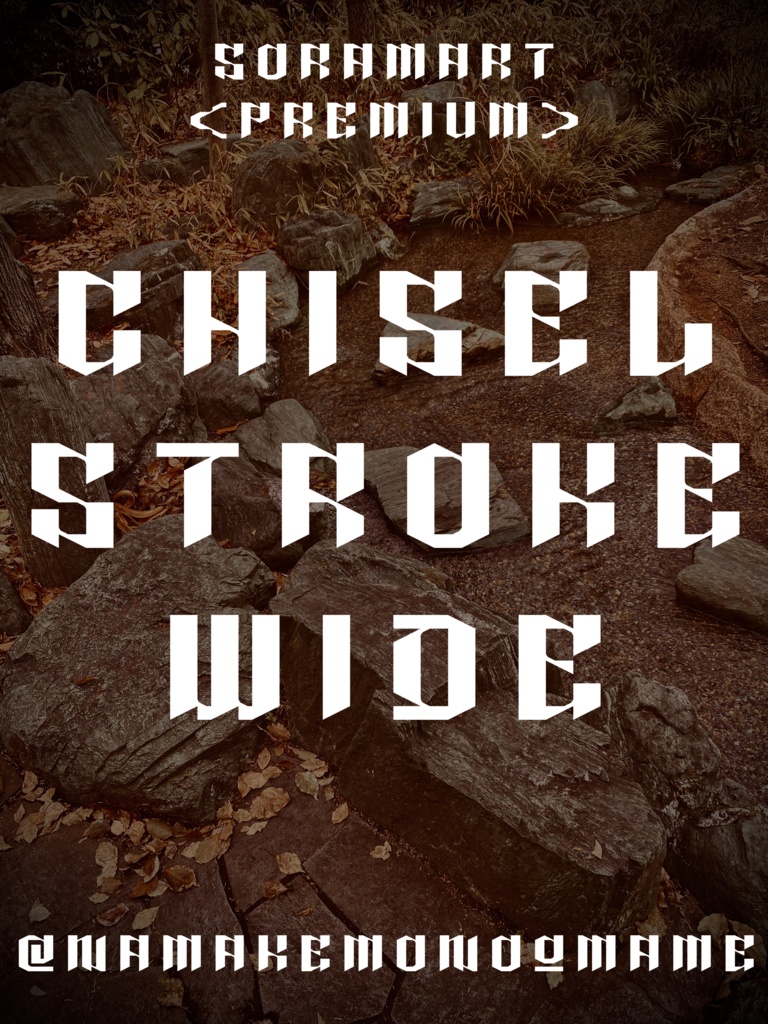
そらマートフォントデータ”Chisel Stroke Wide”Digital2,500 JPYAdd to CartBuy a GiftAbout Gift彫刻刀で刻んだような斜線をモチーフにしたフォントの幅広版 "Chisel Stroke Wide" です。 「TrueTypeフォントファイル」という形式です。 ダウンロードした後、Zipファイル内のデータをインストールしてお使いください。 このフォントは商用利用可となっております。 お客様の制作・創作活動のお役に立てれば幸いです。 ※使用上の注意事項などは、添付のReadmeをお読みください。 ※このフォントは有料販売専用商品です。そらマートVisit FANBOX!Fontsフォントデータ”Hazy Flap”そらマート0 JPYFontsフォントデータ”Amber Nouveau Tight”そらマート2,500 JPYFontsフォントデータ”Amber Nouveau Wide”そらマート2,500 JPYFontsフォントデータ”Amber Nouveau”そらマート2,500 JPYFontsフォントデータ”RANMMA Drive”そらマート2,500 JPYFontsフォントデータ”Dandy Laser Max”そらマート2,500 JPYFontsフォントデータ”Dandy Laser”そらマート2,500 JPYFontsフォントデータ”Bubblegum Beat”そらマート2,500 JPYFontsフォントデータ”Caltrop Serif LLL”そらマート2,500 JPYFontsフォントデータ”Caltrop Serif LL”そらマート2,500 JPYFontsフォントデータ”Caltrop Serif”そらマート2,500 JPYFontsフォントデータ”Tonik Crate Super Long”そらマート2,500 JPYFontsフォントデータ”Dot Eat Bug Acid”そらマート2,500 JPYFontsフォントデータ”Dot Eat Bug Mild”そらマート2,500 JPYFontsフォントデータ”Dot Eat Bug”そらマート2,500 JPYFontsフォントデータ”Solid Voltage Strike”そらマート2,500 JPYFontsフォントデータ”Solid Voltage”そらマート2,500 JPYFontsフォントデータ”Henge Edge Rock”そらマート2,500 JPYFontsフォントデータ”Henge Edge Tall”そらマート0 JPYFontsフォントデータ”Henge Edge”そらマート0 JPYSee More